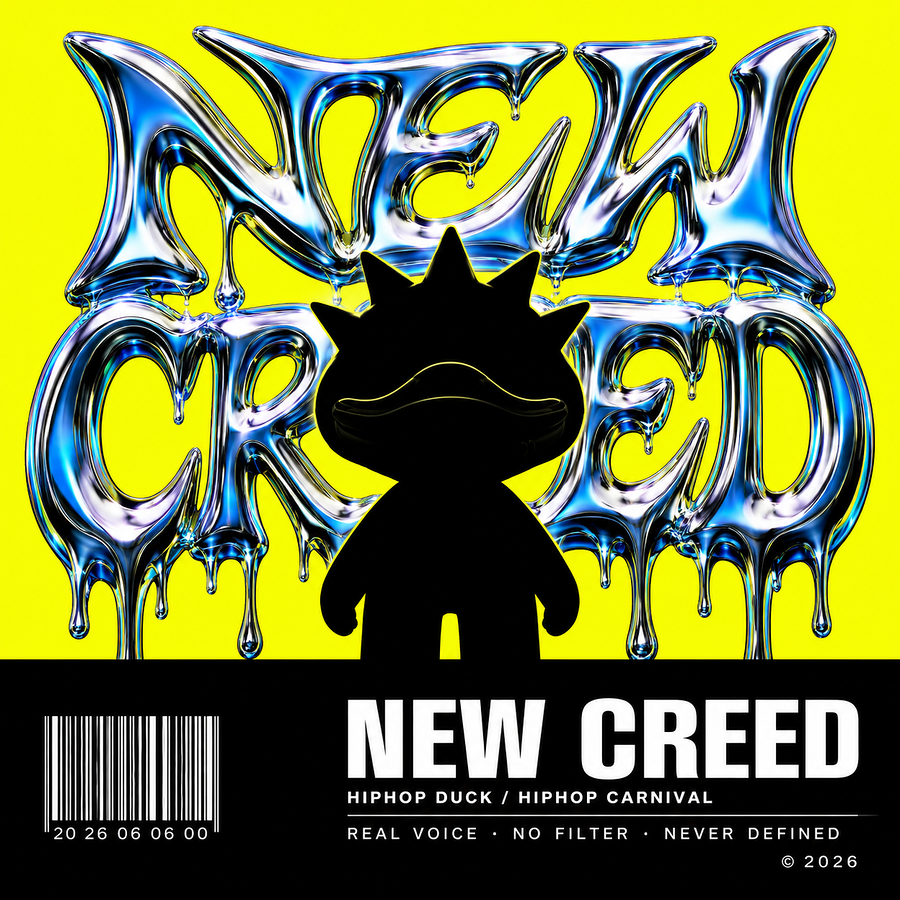
液态金属字体X黑胶封面设计
黑胶唱片封面设计,1:1 正方形构图,主题为 “NEW CREED ”。采用强烈的上下横向分割:上方约三分之二为高饱和电光柠檬黄,下方约三分之一为纯黑信息面板,分界线水平、锐利、干净。 黄色区域中央是大型抽象流体瀑布NEW CREED, 字体有尖有圆,不规则流动感,上下排字体底部都有融化低落的感觉,字体边缘对齐(占据画面大部分画幅,两行),采用 3D 渲染的铬金属材质,表面呈青蓝色虹彩反射效果。星形前方居中叠加一只近乎纯黑的 HIPHOP DUCK 正面剪影,角色从黄色区域延伸至黑色分界处,遮挡部分星形中心。保留夸张鸭嘴、无眼面部和头顶六根尖刺等核心识别特征,造型简洁完整,不呈现内部细节,仅以深黑剪影形成强烈明暗对比,传递冷峻、觉醒、不被定义的精神感。 底部纯黑面板保持克制的信息排版:左下加入细长白色条形码;中部或右侧以大号白色粗体排版 “NEW CREED”;周围加入小号白字: HIPHOP DUCK / HIPHOP CARNIVAL REAL VOICE · NO FILTER · NEVER DEFINED © 2026 整体配色严格限定为电光黄、青蓝虹彩金属、纯黑与白色。融合 Y2K、赛博朋克、液态铬金属、实验编辑设计、DIY 朋克传单与地下嘻哈唱片文化,视觉高对比、直接、锋利,具有独立音乐厂牌与收藏级黑胶封套质感。避免规整对称星形、实心星形、普通扁平五角星、复杂背景、过多装饰、写实场景和多余人物。